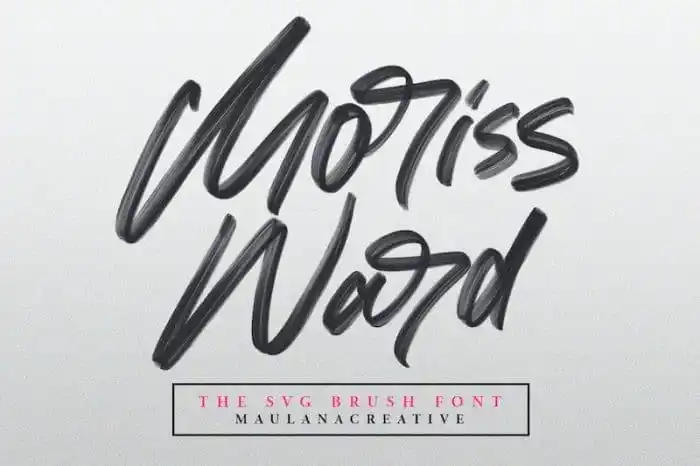
Moriss Ward Brush Font – Download Grátis
A Moriss Ward Brush Font é uma fonte criada com facilidade, oferecendo uma sensação descontraída e naturalmente escrita. Este design inovador foi produzido pela Maulana Creative, ideal para variados formatos de comunicação gráfica. Com o seu estilo relaxado e autêntico, esta fonte é perfeita para criações em qualquer projeto que inclua assinaturas, cartões de papelaria, logotipos, design tipográfico, citações para revistas ou livros, cabeçalhos de site, panfletos, roupas e embalagens. Não importa o tipo de projeto que você está desenvolvendo, a Moriss Ward Brush Font é uma escolha inteligente para se tornar uma parte essencial do seu design.